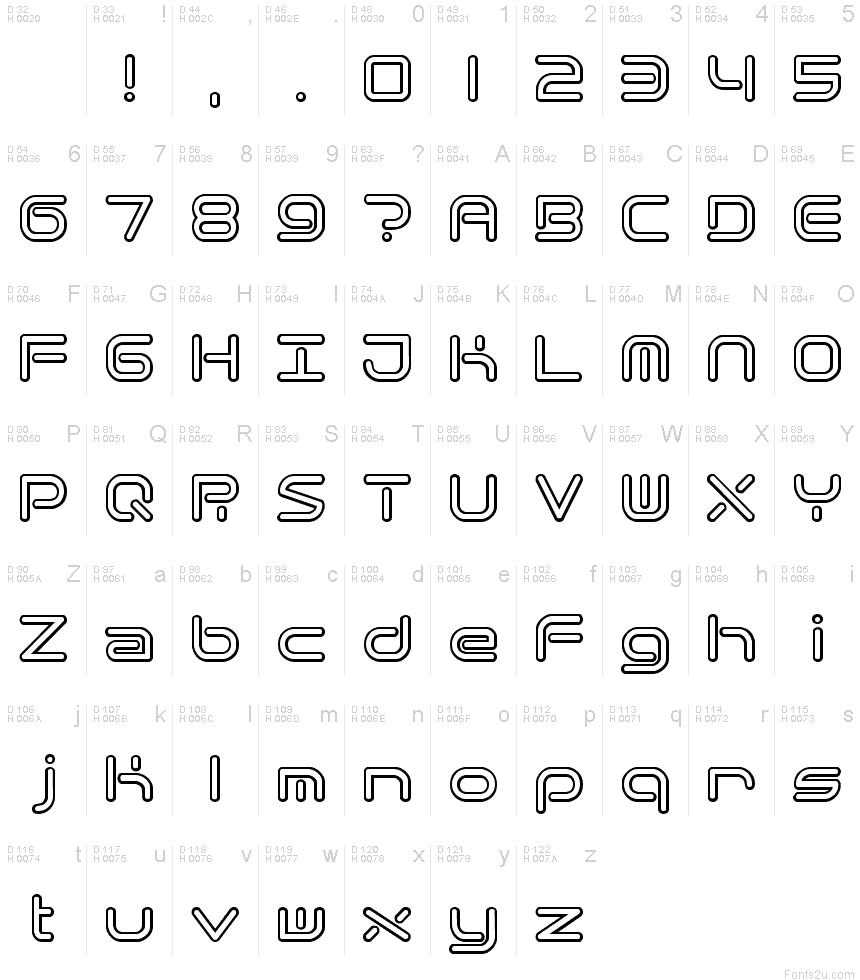
Quantum Round Hollow od ÆNIGMA Fonts to darmowy, futurystyczny font display o miękkim, kosmicznym klimacie. Litery zbudowane są z grubych, zaokrąglonych ścieżek z otwartymi wnętrzami, co nadaje alfabetowi rurowy, ciągły wygląd, przypominający bardziej podświetlone obwody niż zwykłe liternictwo.
Dzięki temu idealnie pasuje do plakatów sci-fi, okładek albumów elektronicznych, tytułów gier, grafik na wydarzenia technologiczne i opakowań opartych na logo. Jako darmowy font do krótkich nagłówków, plansz tytułowych czy logotypów, wnosi płynny klimat retro-futuryzmu, a zaokrąglone kontury sprawiają, że nawet proste słowa nabierają animowanego, rysunkowego charakteru.
Quantum Round Hollow (BRK)